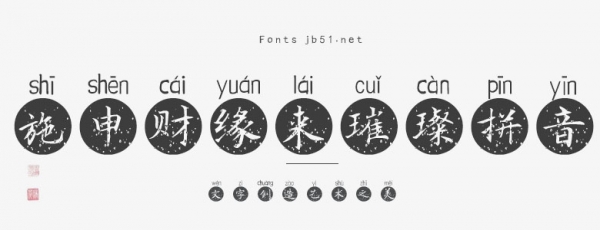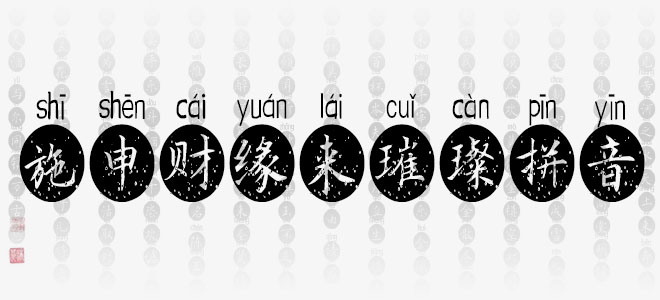
施申財(cái)緣來(lái)璀璨拼音是一款書(shū)寫(xiě)很新穎的字體,自帶拼音標(biāo)注效果,具有強(qiáng)烈的視覺(jué)沖擊力。適用于海報(bào)、電商海報(bào)設(shè)計(jì)、店鋪設(shè)計(jì)、標(biāo)志設(shè)計(jì)、字體設(shè)計(jì)等領(lǐng)域。
施申財(cái)緣來(lái)璀璨拼音